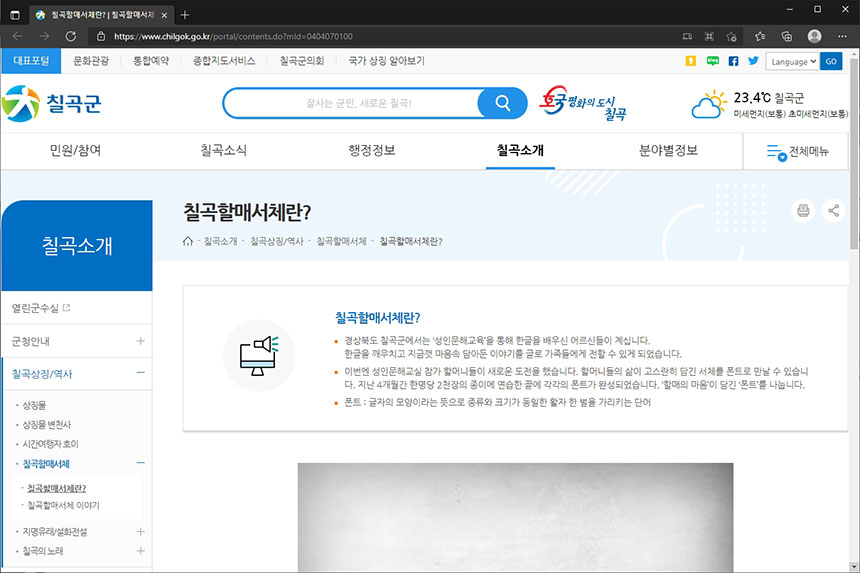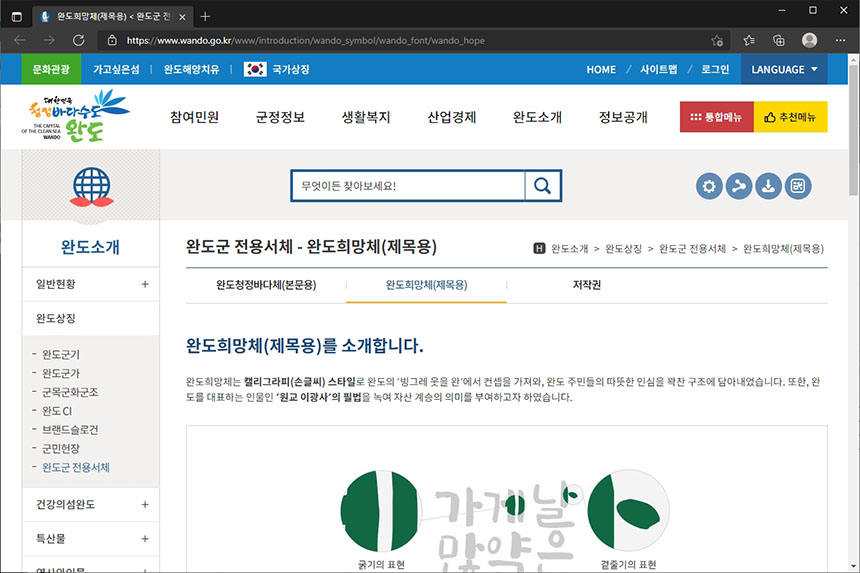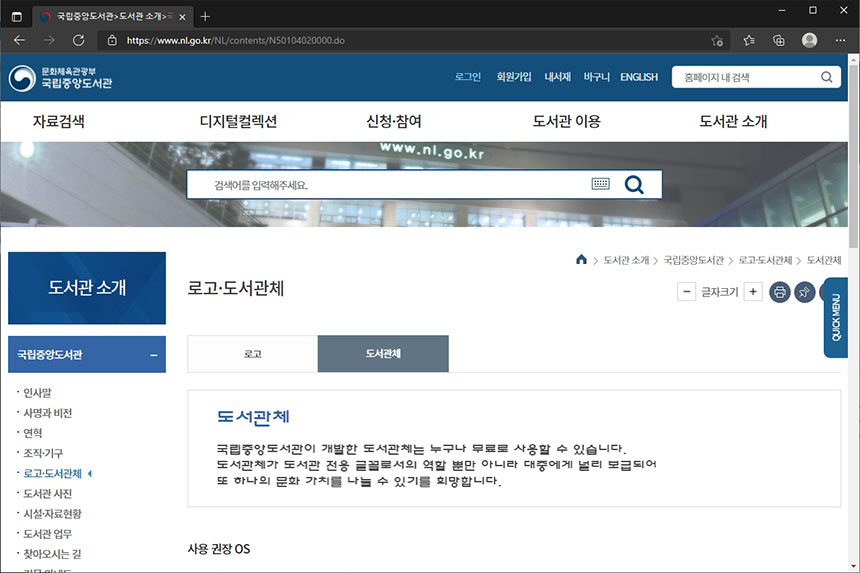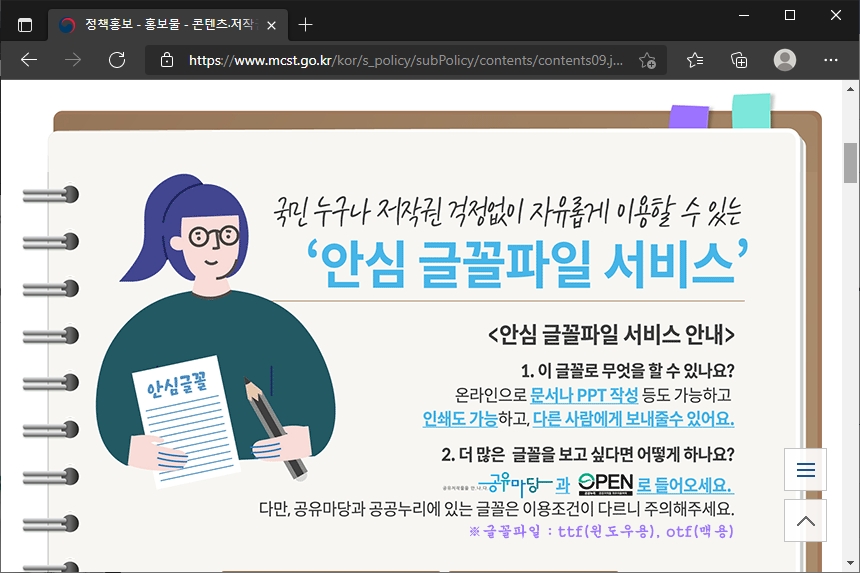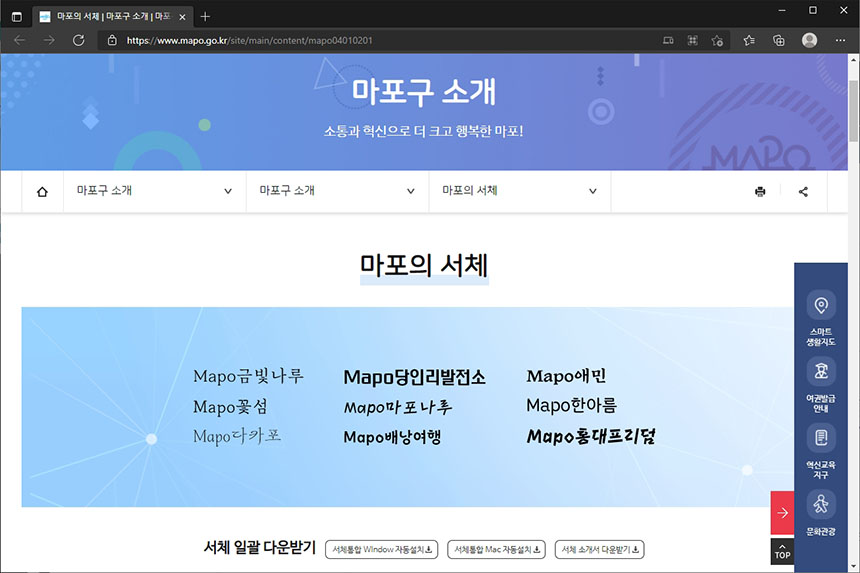
MS가 선택한 무료 한글 폰트 12종과 안심 글꼴 총정리!
유튜트나 블로그 등에 업로드할 동영상이나 사진 콘텐츠를 제작하다 보면 가장 신경 쓰이는 부분 중의 하나는 바로 폰트라고 할 수 있습니다. 저작권에 관련 문제가 발생할 수 있기 때문에 많은 분들이 편리하게 사용할 수 있는 상업적 무료 폰트들을 찾아 헤매고 있습습니다. 그럼 이번 포스팅에서는 마이크로소프트 윈도우에 탑재되는 공공 안심글꼴파일 12종을 살펴보면 155종의 폰트를 무료로 다운로드 받는 방법을 확인해 보도록 하겠습니다.
가장 먼저 살펴볼 폰트는 안동엄마까투리체입니다. 둥글둥글한 매력이 있어서 귀여운 캐릭터들과 잘 어울리는 특징을 가지고 있습니다. 그리고 상업적으로 무료 사용은 가능하지만 출처 표기를 해야 합니다.
다음에 살펴볼 폰트는 Mapo 꽃섬과 Mapo 배낭여행 그리고 Mapo 디카포입니다. 꽃섬은 약간의 궁서체와같은 느낌이고 배낭여행은 안동엄마까투리체처럼 둥글둥글한 매력이 있습니다. 특히 디카포 폰트가 독특한 느낌이라고 생각되었습니다.
다음은 칠곡할매서체 5종입니다. 칠곡할매 김영분체, 칠곡할매 권안자체, 칠곡할매 이원순체, 칠곡할매 이종희체, 칠곡할매 추유을체으로 구성되어 있는데요. 상당히 의미가 있는 폰트라고 생각되었습니다.
다음에 살펴볼 폰트는 국립중앙 도서관체입니다. 넓직넓직한 주는 편이어서 제목 등에 사용하면 좋을 것으로 예상합니다. 중앙도서관을 조금 다녀보신 분들이라면 익숙할 것 같습니다.
마지막 폰트는 완도희망체입니다. 캘리스라피 스타일로 제작되어서 무언가 포인트가 되는 글씨를 사용하고 싶을 때 활용하면 좋을 만한 서채라고 생각이 되었습니다.